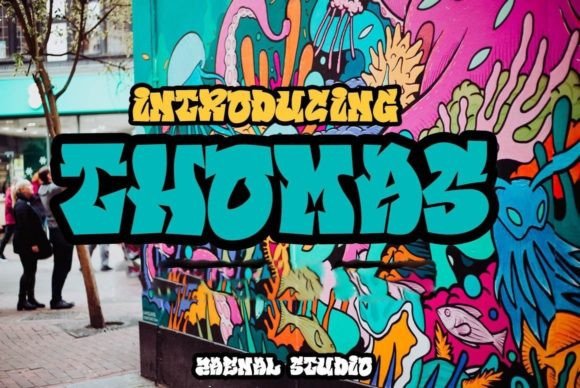
Thomas
Thomasのような高品質の素材をお探しの場合、このプレミアムパッケージはクリエイティブなプロジェクトに素晴らしい選択です。
精密に作られたThomasは、クリーンなベクター、滑らかなタイポグラフィ、そして安心のための商用ライセンスを提供します。
POD(オンデマンド印刷)製品、結婚式の招待状、またはソーシャルメディアのグラフィックを作成している場合でも、Thomasは理想的です。